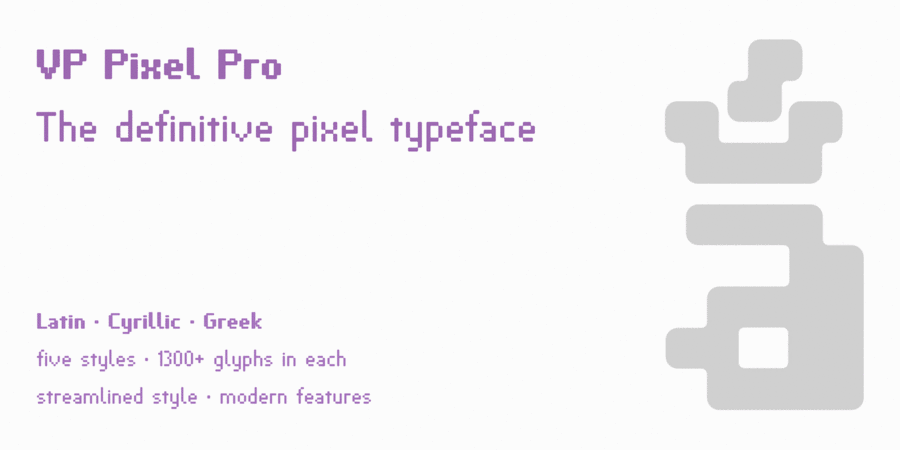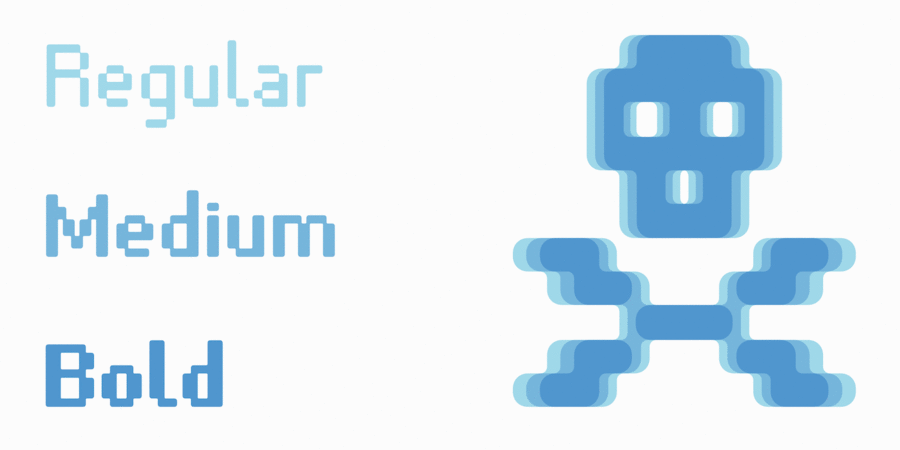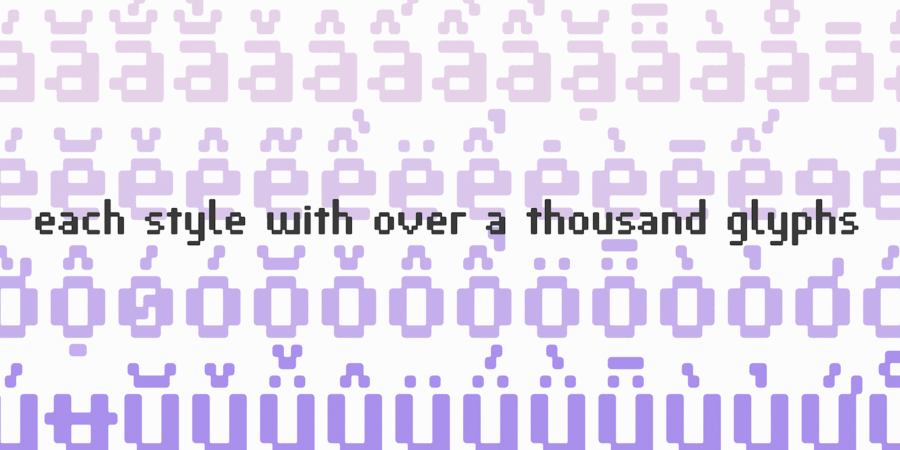
Опис гарнітури VP Pixel Pro розроблено як остаточний стандарт для піксельних шрифтів. Маючи понад 1300 символів у кожному стилі, він забезпечує повну підтримку більш ніж 230 мов, що дає змогу легко локалізувати вашу роботу в усьому світі. Усі шрифти цього сімейства включають великі, рядкові та капітель для латинського алфавіту, а також розширені набори кирилиці та грецького алфавіту, численні набори цифр, великий набір діакритичних знаків, розділових знаків та інших символів. Включено численні функції OpenType, такі як кілька вертикальних позицій, діагональні дробові форми, додаткові косі нулі, німускульні та маюскульні цифри, а також контекстні альтернативи. Універсальний та вдосконалений, VP Pixel Pro стане вашим улюбленим піксельним шрифтом незалежно від обраної задачі.
Шрифт розробив Вал Калініч у 2019 році.
Особливості сімейства шрифтів VP Pixel ProХіт десятиліття:
Асоціації з сімейством шрифтів VP Pixel ProОсобистість і характер гарнітури:
автоматичний, комп'ютерний, електронний, машинний, матричний, інженерний, байдужий, точний, М'який, гладенький, гострий, різкий
електроніка, автоматика, код, програмування, інженер, комп'ютер, робот, IT, айтішник, айті, андроїд, залізо, гра, фантастика, математика, технології, наука, хакер, рентген, комп'ютерна гра Гарнітура асоціюється з віком: